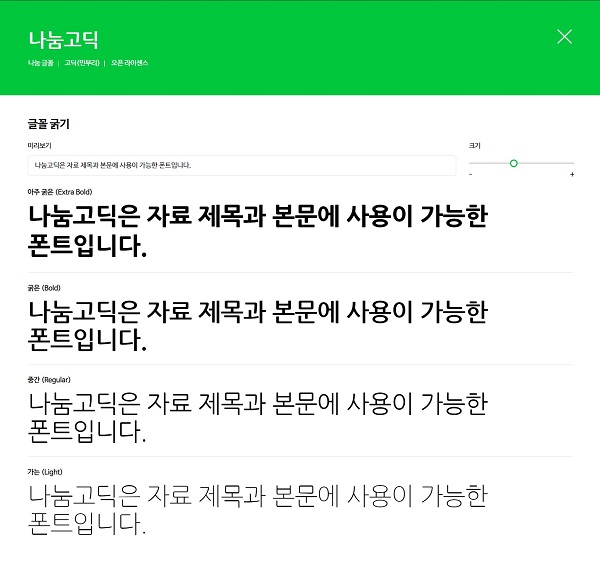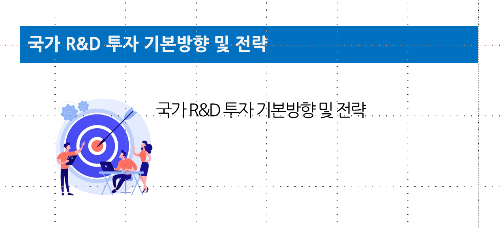
이번에 소개해드릴 폰트는 나눔고딕체입니다.
네이버에서 2008년부터 한글캠페인을 시작하면서 탄생시킨 나눔글꼴에서
한글, 워드, 파워포인트 등 문서 작업 시 제목과 본문 모두에 사용이 가능한 폰트입니다.
두께감이 있고 제목과 본문 모두에 활용이 가능한 폰트를 찾고 있다면 ?
저도 자료를 만들 때 자주 이용하는 폰트입니다.
특히 발표자료나 포트폴리오 작성에 활용하시면 깔끔하게 구성을 하실 수 있습니다.
예시로 포트폴리오에 사용한 내용을 보여드리겠습니다.
폰트 활용하는 방법
이런 Bold, Extrabold, Light로 구분이 되어 있는 폰트들은
글을 먼저 작성하신 다음에 Ctrl+B를 누르거나 굵은 글씨로 설정하시는 것이 아닙니다.
글을 쓰신 후 폰트를 바꿔주시면서 사용하시는 겁니다.
폰트만 잘 활용해서 문서의 구성이 깔끔해 집니다.
자료의 목적과 대상을 생각해보시고 좋은 폰트들을 잘 활용해 보세요.